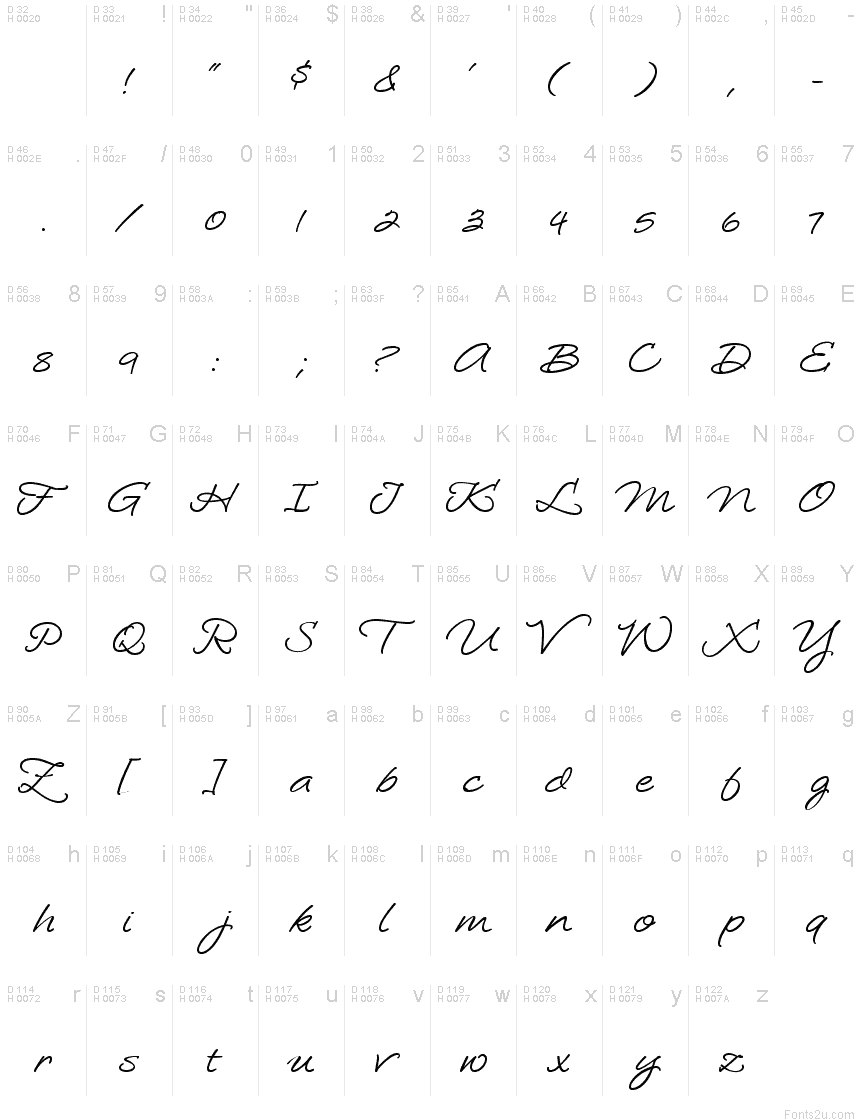
Loosie Script to darmowy kaligraficzny krój pisma z długimi pętlami i zaokrąglonymi łączeniami, dzięki którym litery układają się w jedną, płynną linię. Otwarty, ręcznie rysowany ruch nadaje projektowi lekki, nieformalny rytm, nie tracąc przy tym czytelnej struktury pisma odręcznego.
Loosie Script świetnie sprawdzi się w zaproszeniach ślubnych, kartkach okolicznościowych, logotypach butików, odręcznych cytatach i etykietach, gdzie delikatne wzornictwo łączy osobisty charakter z elegancją. Ten darmowy font pasuje również do krótkich nagłówków i brandingu typu signature, gdy potrzebujesz czegoś pełnego wdzięku, co jednocześnie łatwo łączy się z prostymi układami graficznymi.